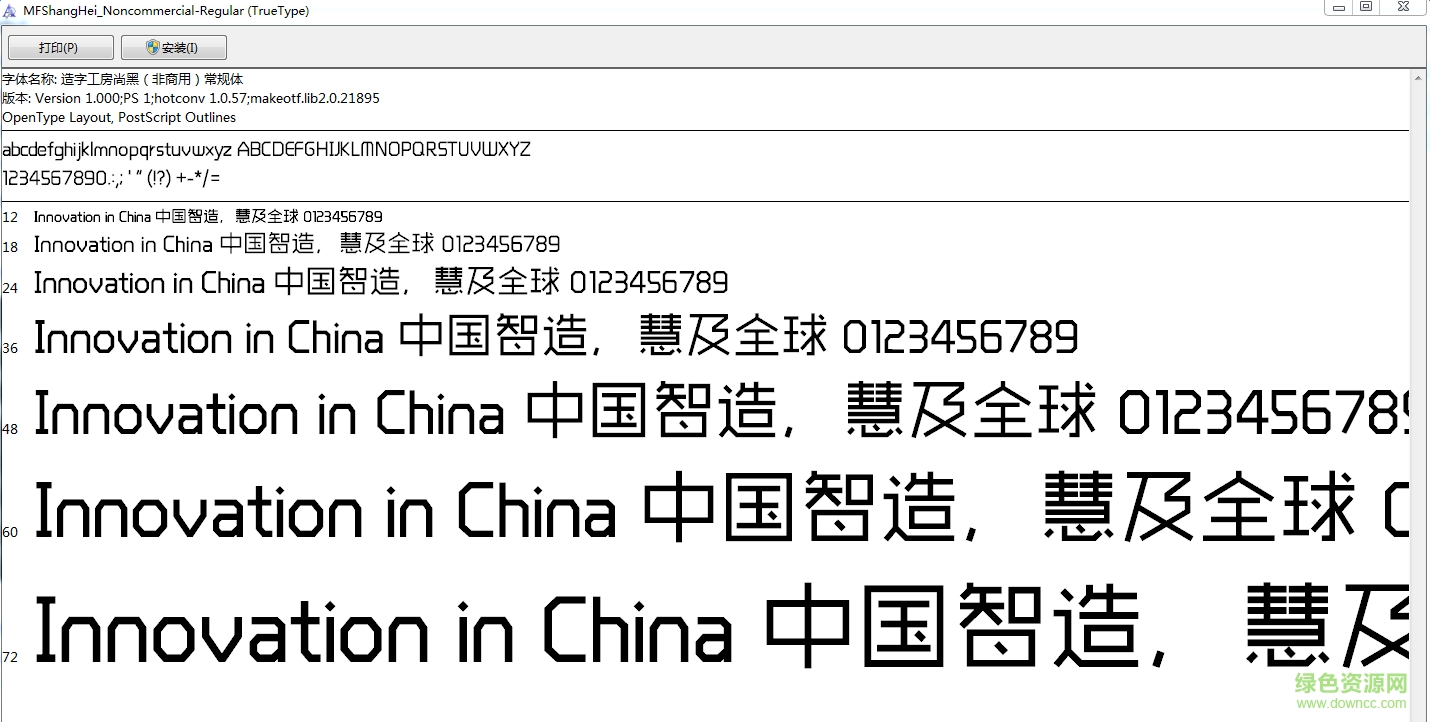
造字工房尚黑體是一款造字工房類古典風(fēng)格字體軟件,尚黑體整體效果工整,卻又不失一點(diǎn)點(diǎn)黑色幽默,適用于各大創(chuàng)意品牌標(biāo)題設(shè)計,也深受廣大書法家的喜愛,還有更多好看字體盡情期待,歡迎到綠色資源網(wǎng)下載體驗(yàn)!
造字工房尚黑字體是一款用于長體,細(xì)體,纖細(xì)體,設(shè)計方面的字體,可用于品牌設(shè)計,創(chuàng)意廣告、藝術(shù)設(shè)計等應(yīng)用。